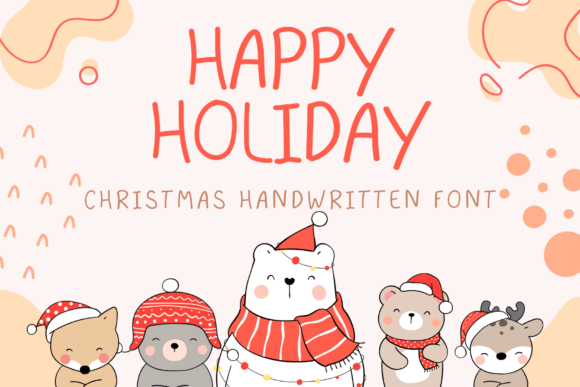
Happy Holiday
適切なデザイン要素を見つけるのは難しい場合がありますが、Happy Holidayは作品を即座に引き立てる優れたコレクションを提供します。
POD(オンデマンド印刷)製品、結婚式の招待状、またはソーシャルメディアのグラフィックを作成している場合でも、Happy Holidayは理想的です。